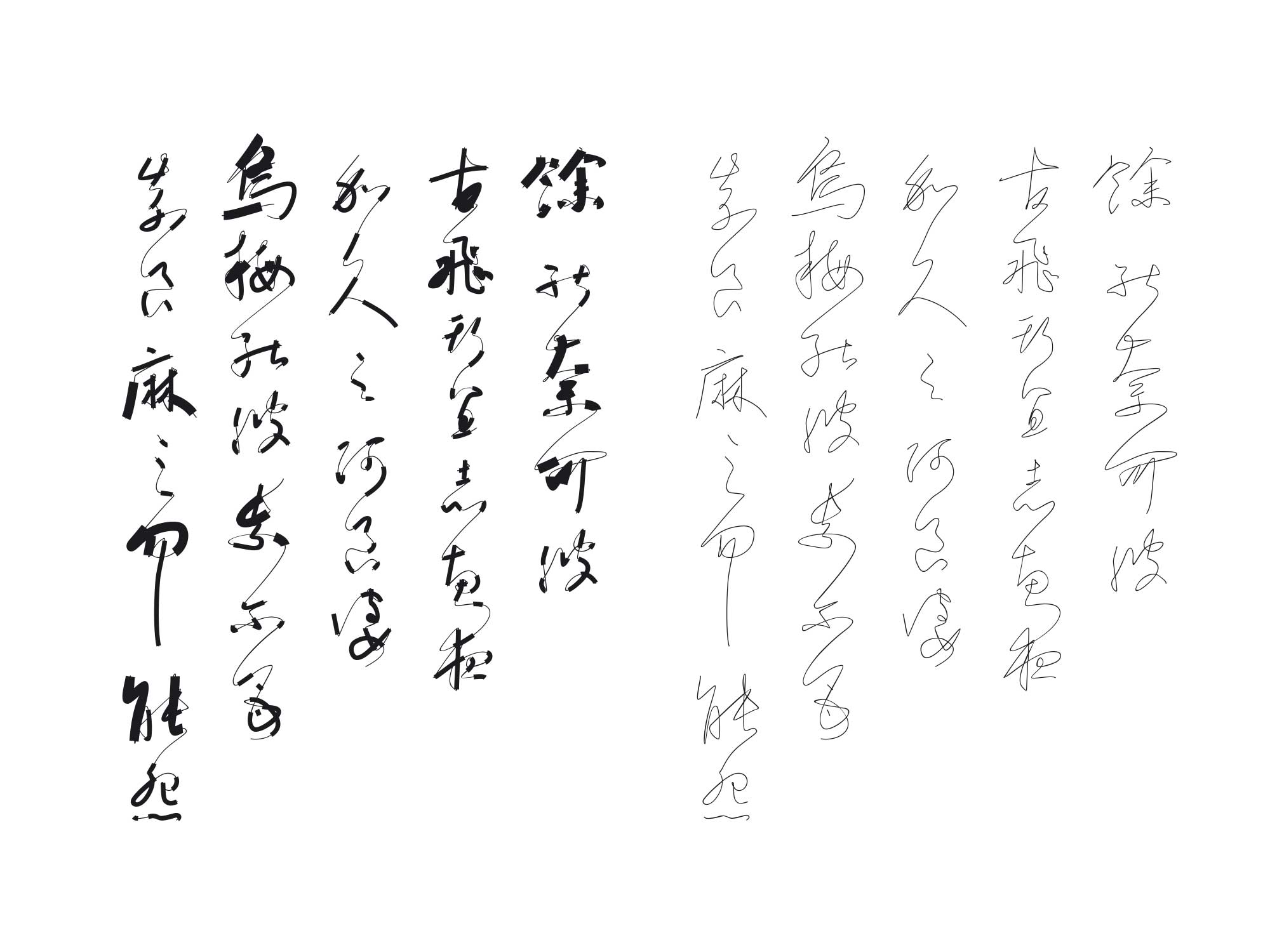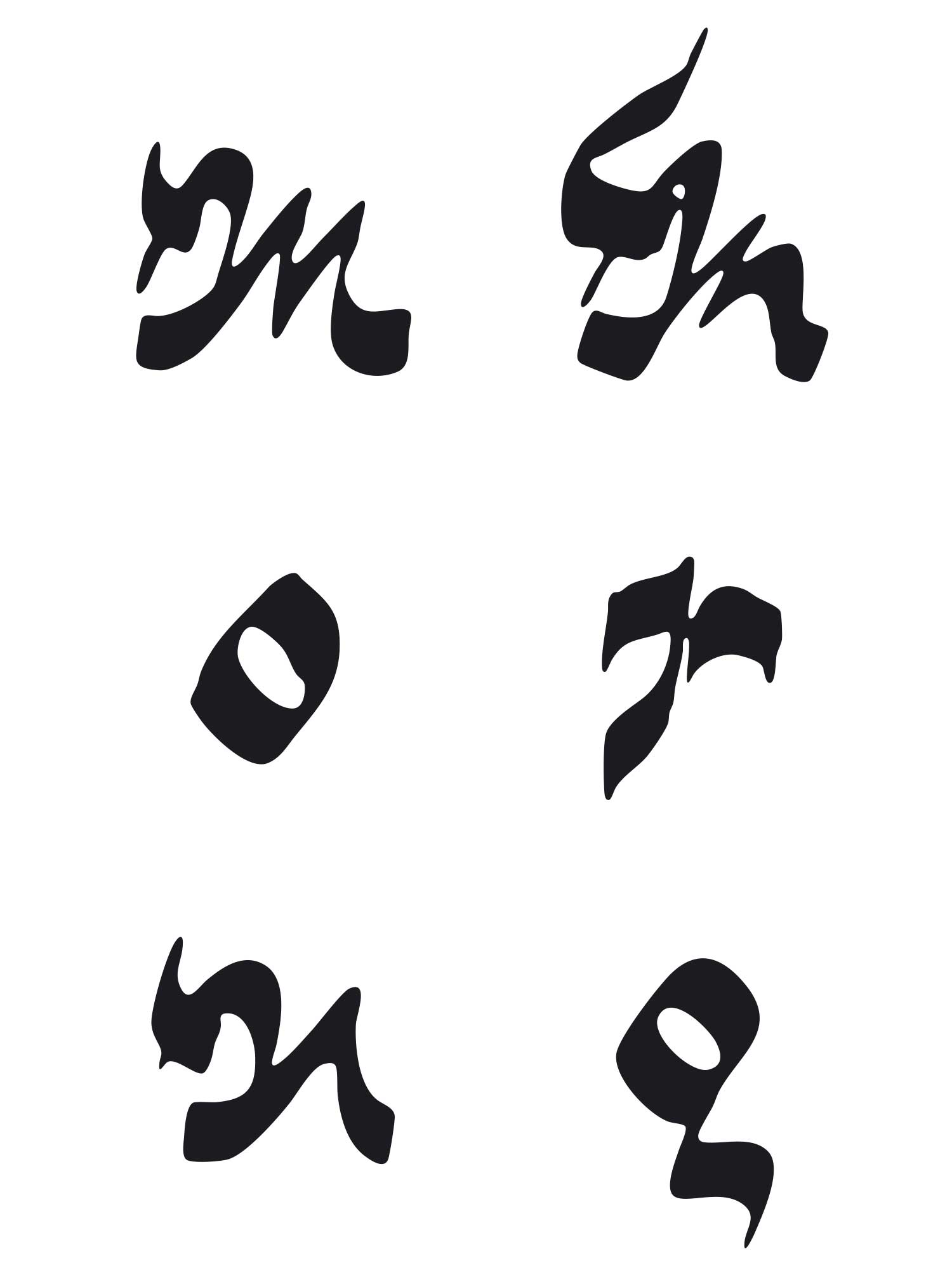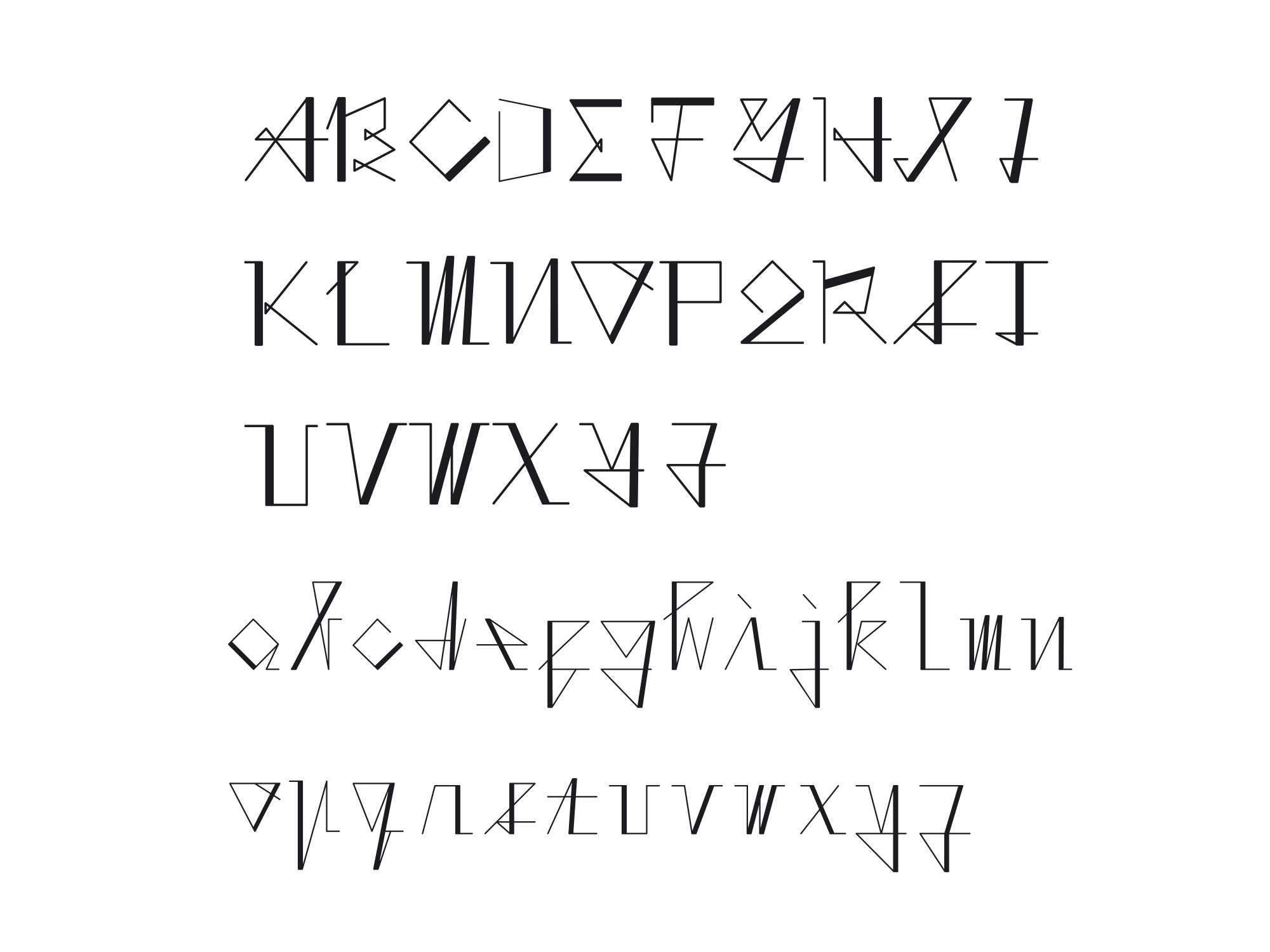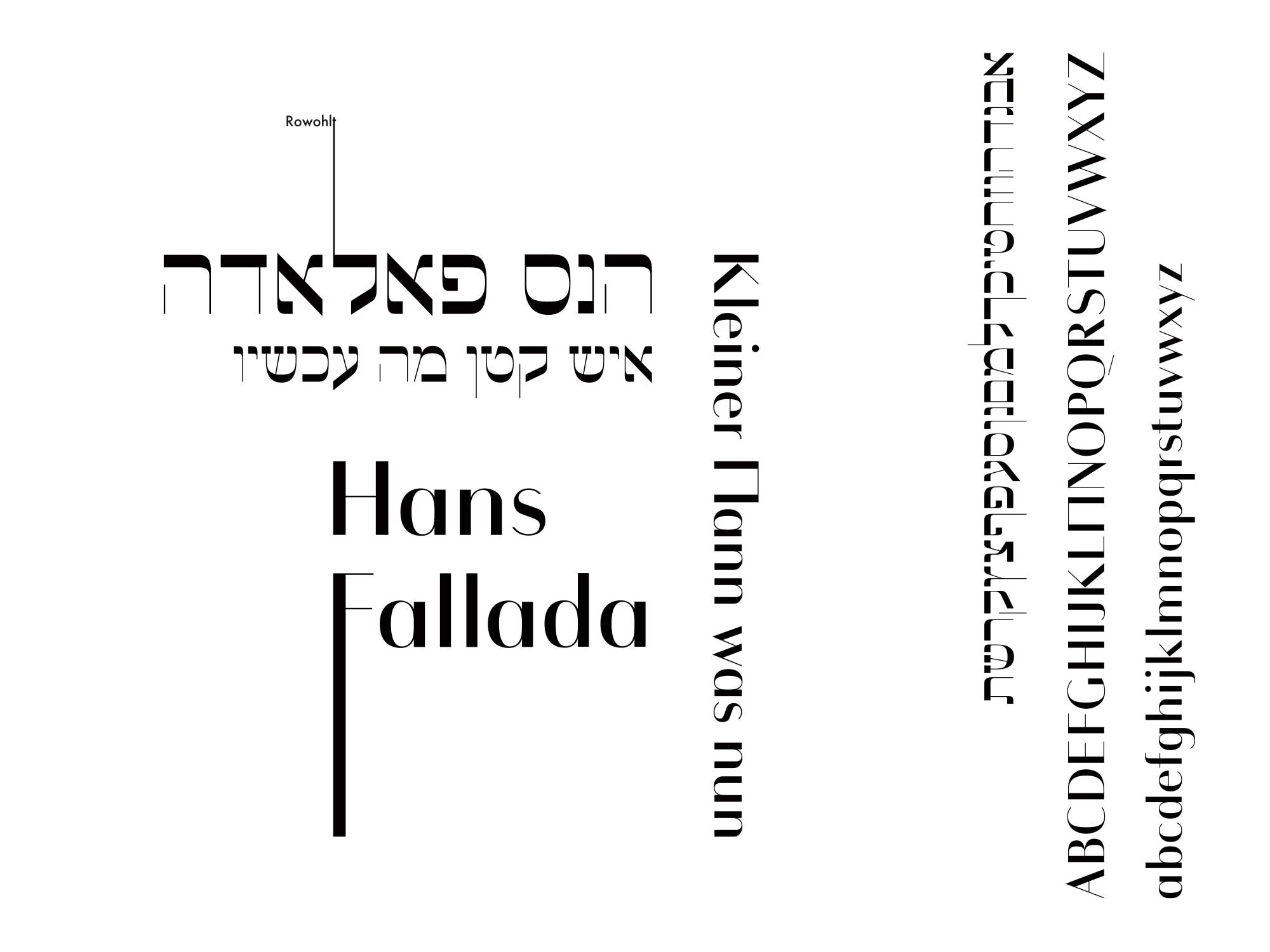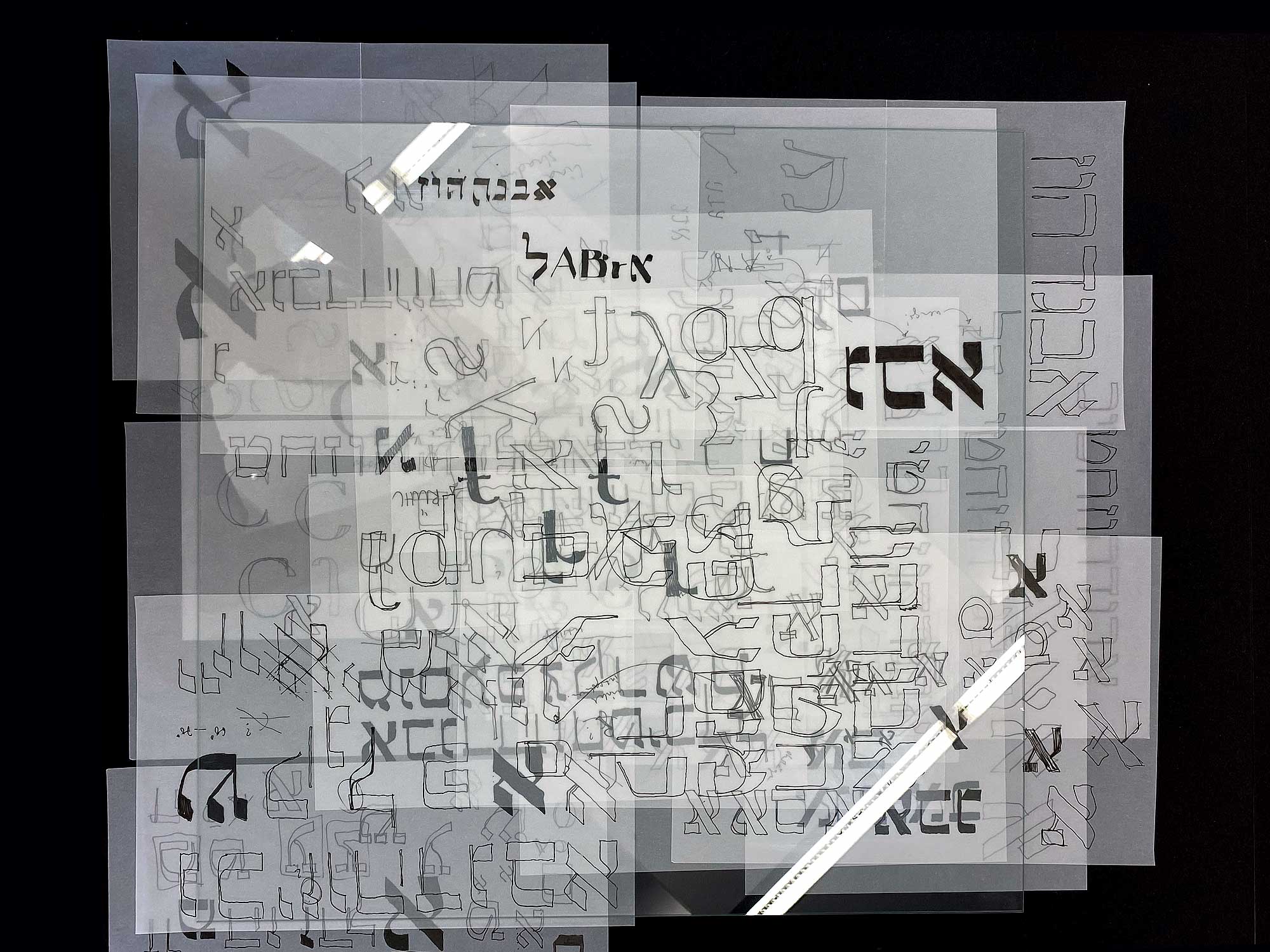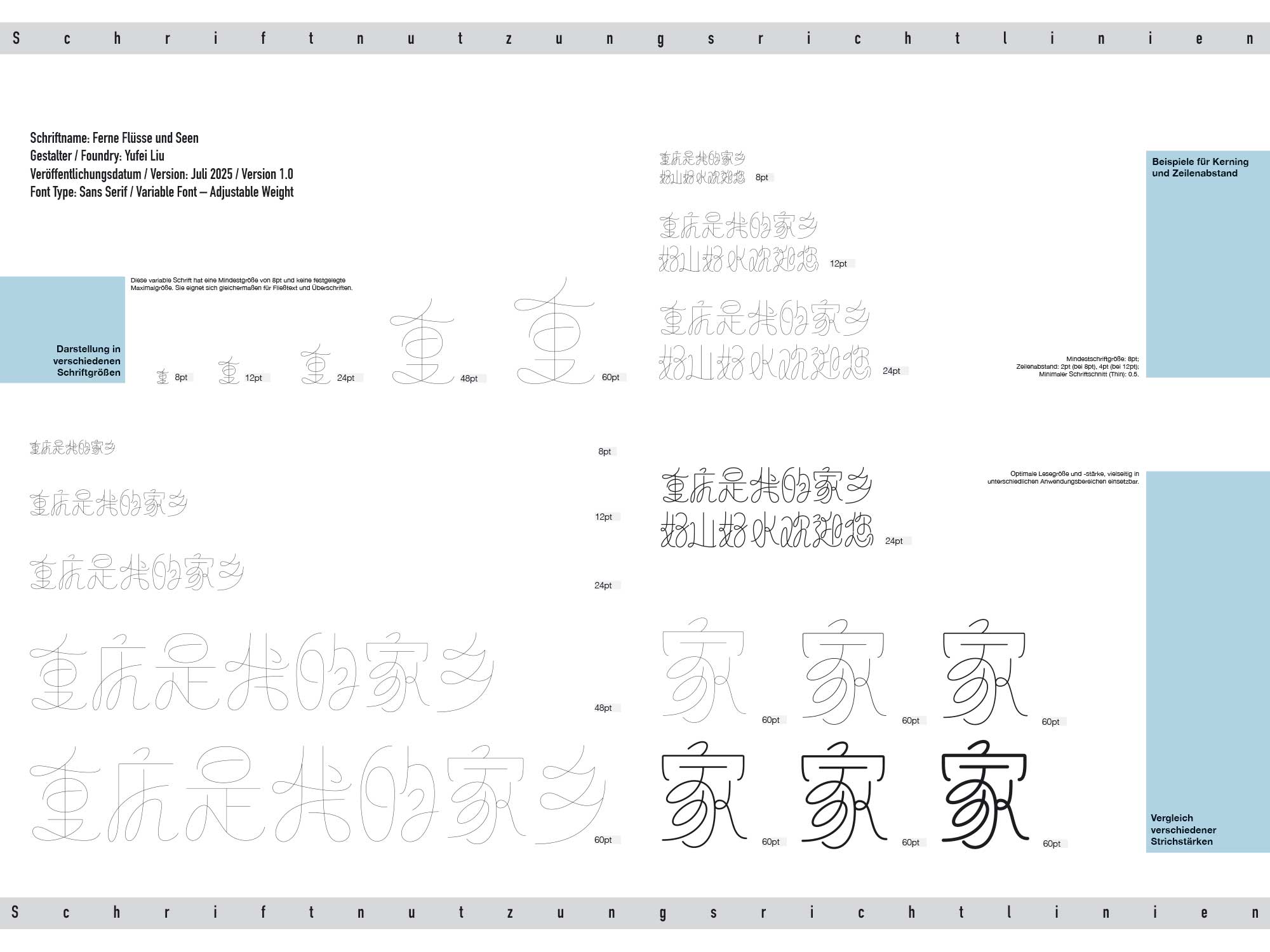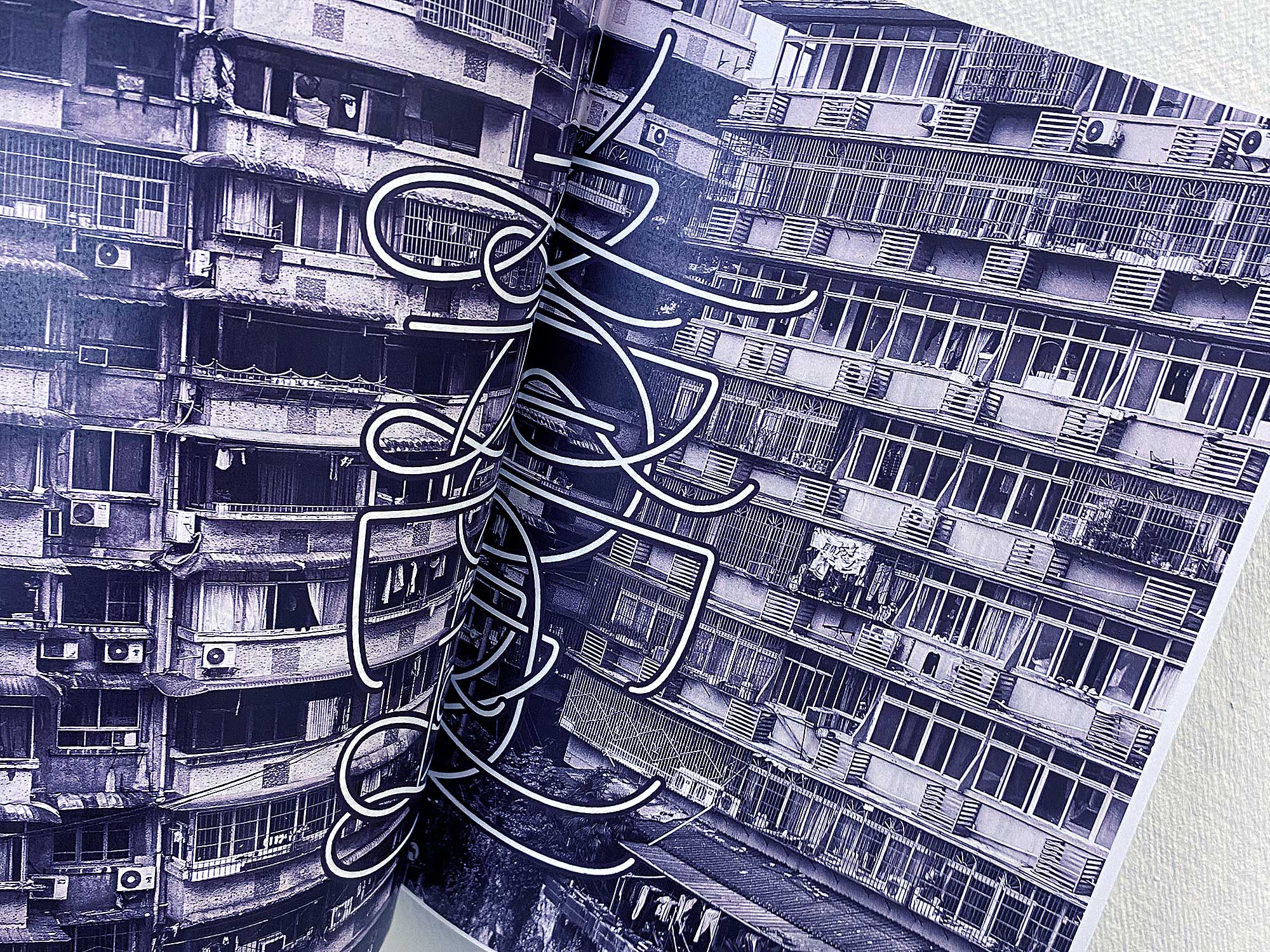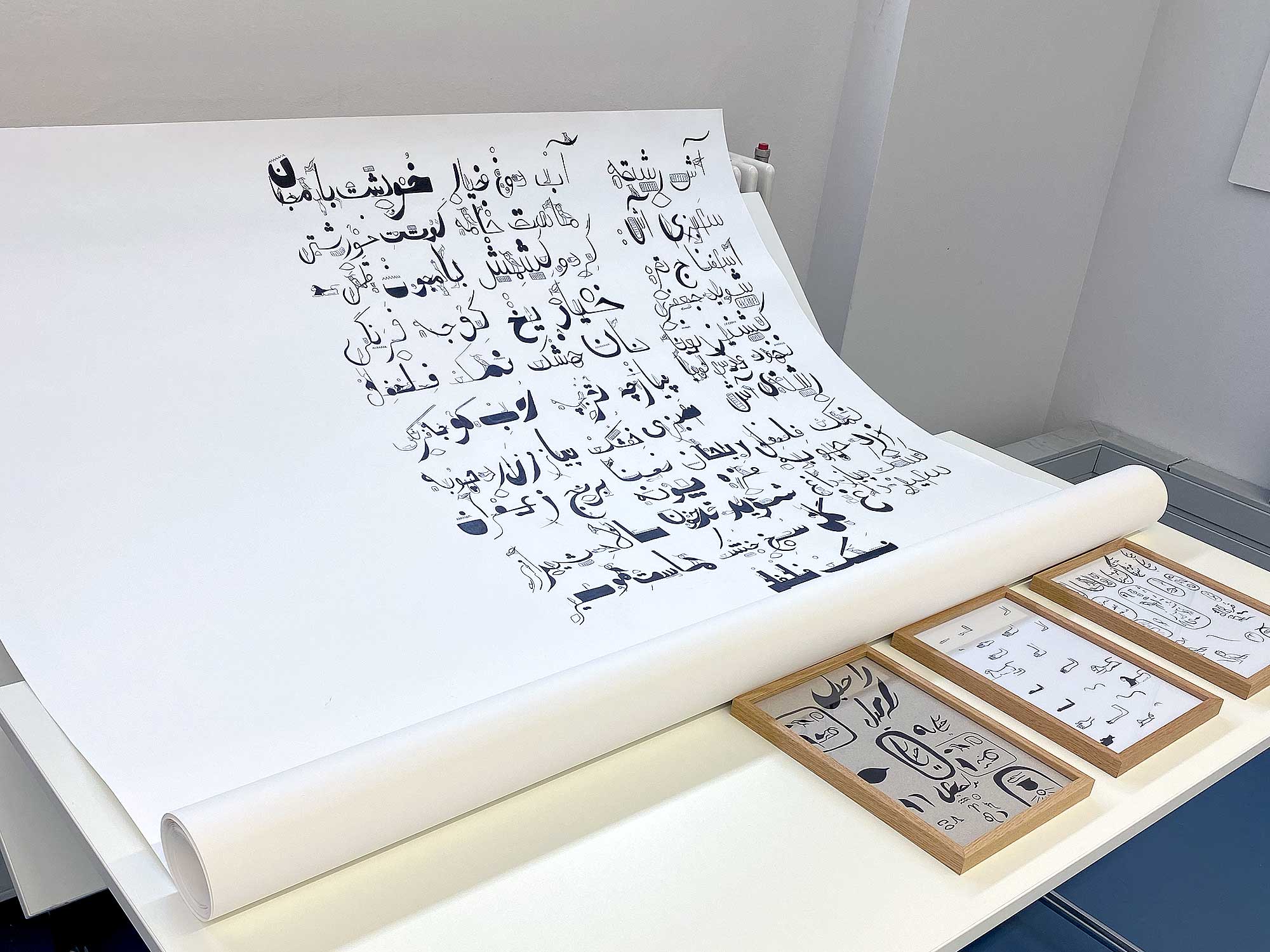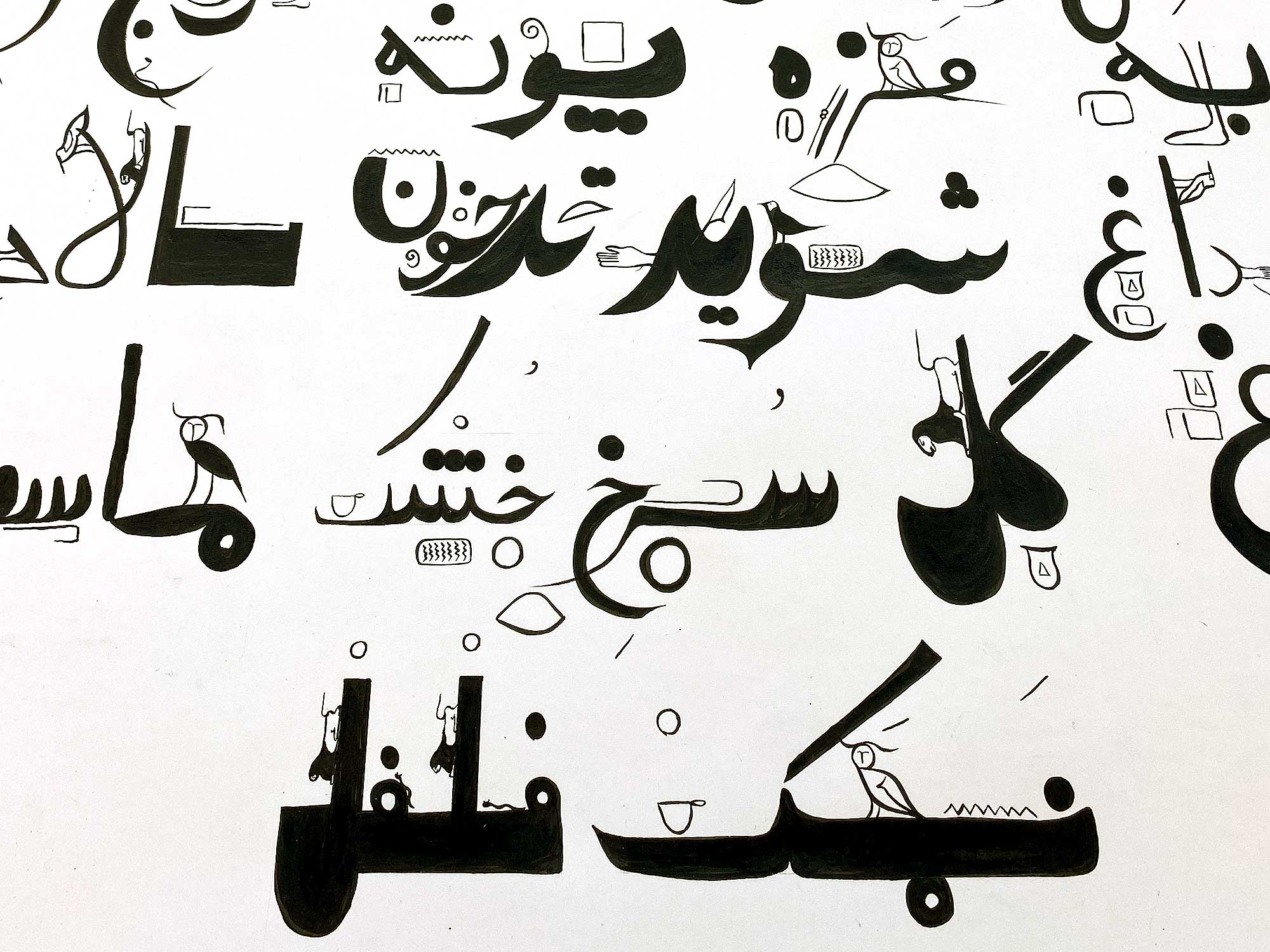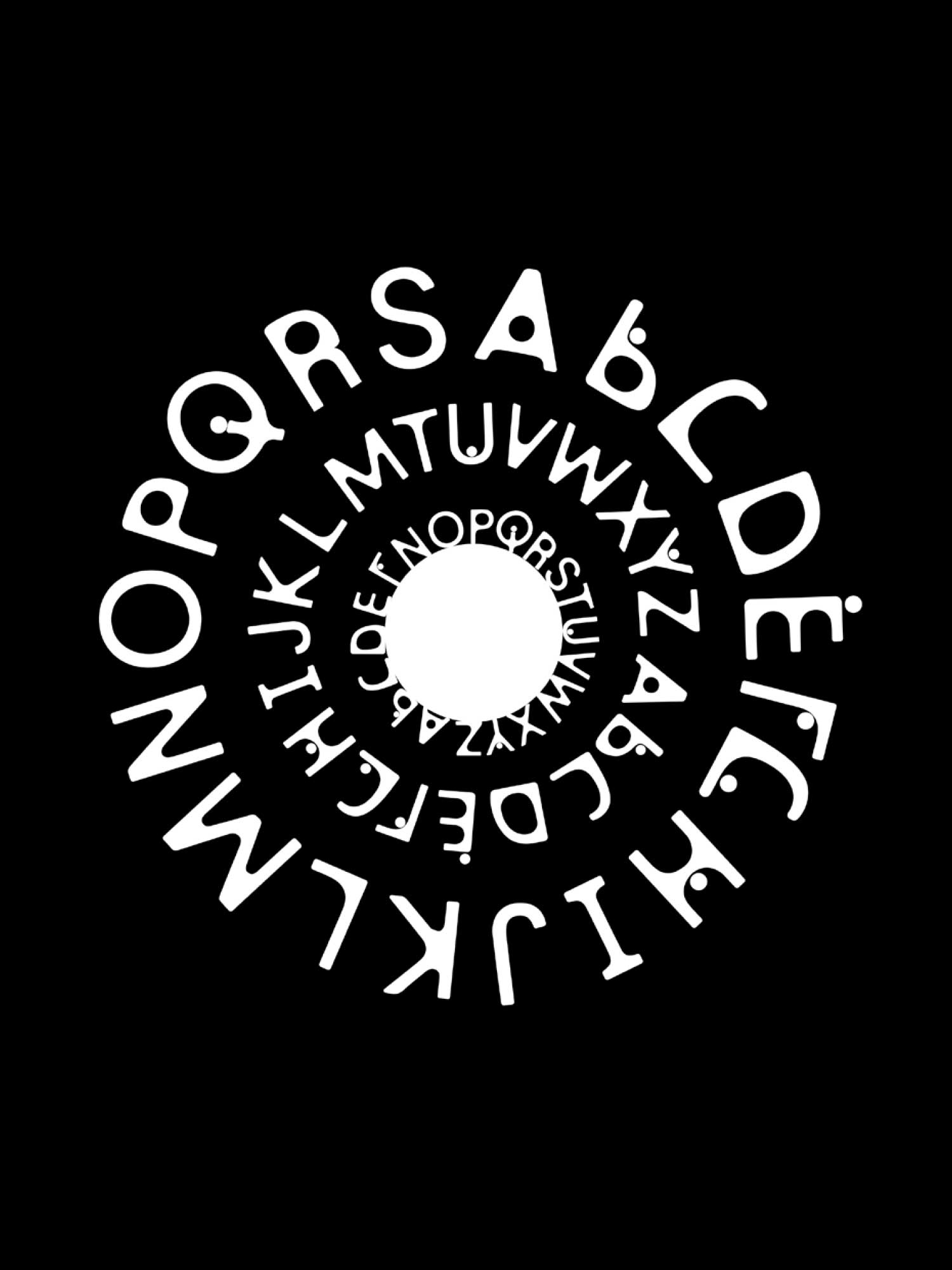
Kurs »Multi-Script Type«
“Multi-script type”
Im Kurs »Multi-Script Type« entstanden kleine Schriftsysteme, die aus mehreren Skripten bestehen sollten. Es stand den Teilnehmenden frei, digital (im Font-Editor oder im Vektorprogramm) oder analog (gezeichnet oder handgeschrieben) zu arbeiten. Von experimentellen Ansätzen bis zum fast fertigen Schriftprodukt ist alles dabei, und ungewöhnliche, kreative Kombinationen und Umsetzungen geben dem Medium Schrift eine transkulturelle Note.
From the “Multi-script type” class emerged little writing systems, consisting of mor than one script. The participants were able to freely choose whether they would work digitally (in a font editor or vector software) or analogously (hand-drawn or written). The results show a variety of different solutions, ranging from experimental approaches to almost ready-to-use font products—unusual, creative combinations and realizations give a trans-cultural twist to the medium of writing.